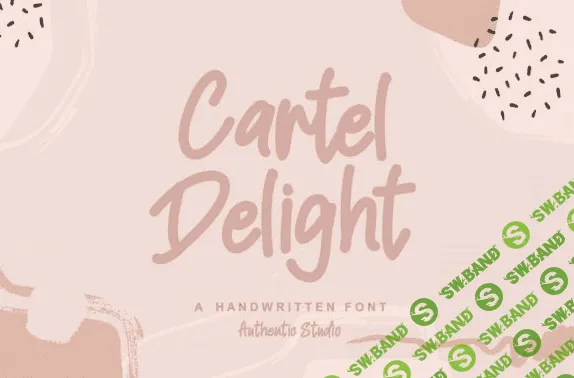
Название: Cartel Delight Font
[Creativefabrica] Cartel Delight Font
Причудливый рукописный шрифт. Этот шрифт отлично подходит для тех, кто любит создавать милые и милые поделки, дизайн, резку, печать, посты в социальных сетях и многое другое!